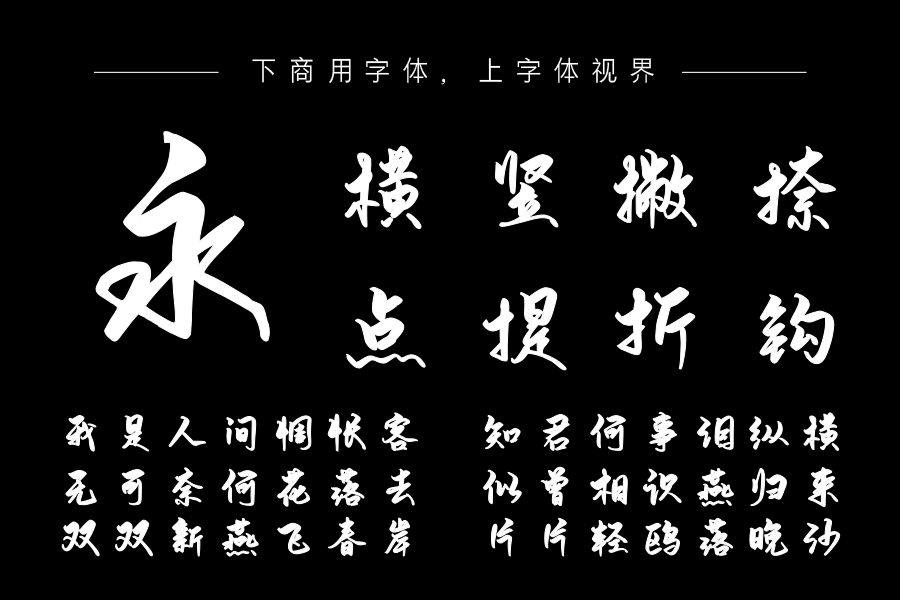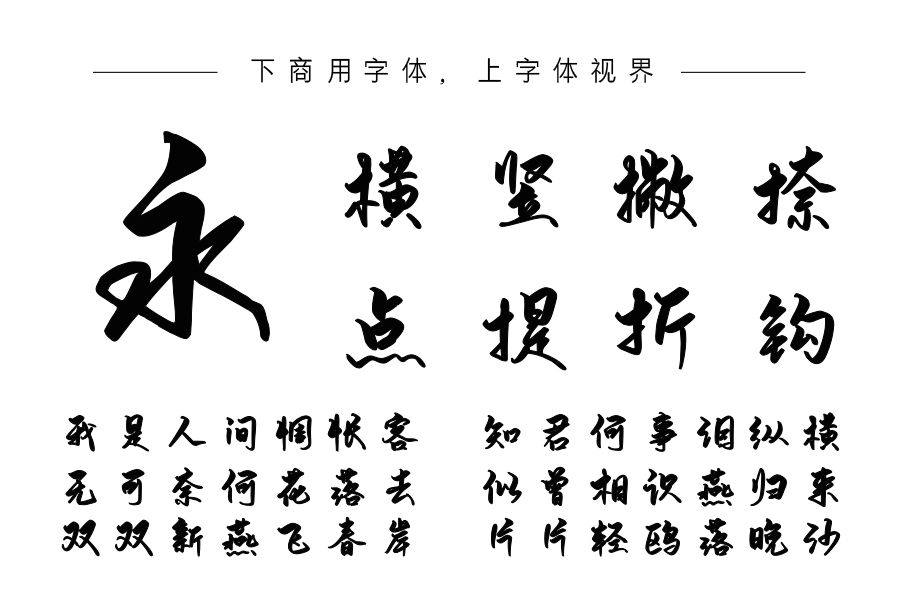
作者结合手绘板的特殊笔触和书法行书笔法,形成了不同于传统毛笔手书字体的新手书风格。 这是一款用手绘板以特殊笔触手绘而成的创意字体,具有和普通手写字质感不同的连绵......购买须知:“下载服务费”与“字体VIP”所获得字体 仅用于个人非商用, 商用请联系付费授权。本字体为电脑用字,手机没有root权限不支持直接手机换字(手机如何root,请自行百度搜索教程)。购买前请先 了解清楚后再付款 ,字体为虚拟产品无法回收 一旦购买不支持退款。